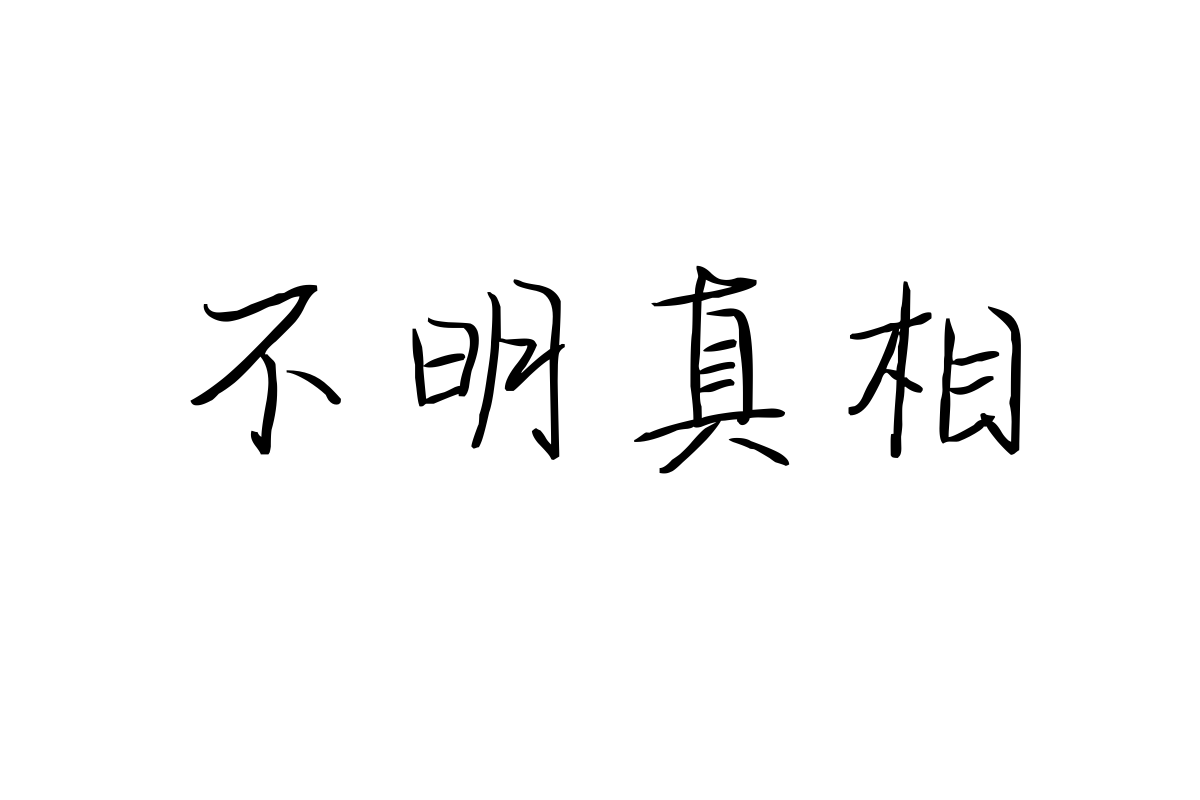
上首迎风手写体是一款具有独特风格的中文字体。这款字体以其独特的笔画结构和流畅的书写线条而闻名,给人一种优雅而自然的视觉感受。
上首迎风手写体的笔画粗细变化丰富,既有粗犷有力的部分,也有细腻柔和的部分。这种对比使得字体在阅读时更加生动有趣,能够吸引读者的注意力。
此外,上首迎风手写体还采用了一些特殊的装饰元素,如波浪线、曲线等,这些元素使得字体更具艺术感和美感。
总的来说,上首迎风手写体是一款非常独特且富有个性的中文字体,适合用于需要展现个性和创意的场合。